2023 年 30 种最佳经典字体(免费和付费)
已发表: 2023-09-20您是一名平面设计师,正在寻找完美的字体来增强您的设计项目吗? 别再犹豫了!
在这篇博文中,我们将分享 2023 年 30 种最佳经典字体,包括免费和高级选项。 但在我们深入之前,您可能想知道为什么经典字体在设计中如此重要。
嗯,经典字体经受住了时间的考验,并因其永恒和优雅的吸引力而继续被广泛使用。 通过将这些字体合并到您的项目中,您可以提升整体设计并给观众留下持久的印象。
现在,我们来谈谈您对本文有何期望。 我们精心挑选了 30 种最佳经典字体供您探索,从不会花太多钱的免费选项到为那些寻求更独特和独特外观的人提供的高级字体。
对于每种字体推荐,我们都会为您提供关键信息,例如其风格、多功能性和流行度,以便您根据您的具体设计需求做出明智的决定。
在本文中,我们的目标是帮助您找到完美的字体,不仅可以增强项目的视觉吸引力,还可以有效地传达您的信息。
无论您是在进行徽标、网站设计还是任何其他创意工作,正确的字体都可以发挥重要作用。 因此,坐下来,放松一下,准备好发现 2023 年 30 种最佳经典字体,它们将把您的设计项目提升到新的高度。
最佳高级经典字体
希望以精致和永恒的优雅来提升您的设计? 我们精心挑选的最佳优质经典字体就是您的最佳选择。 深入研究并发现完美的字体,让您的项目变得栩栩如生!
去风尚
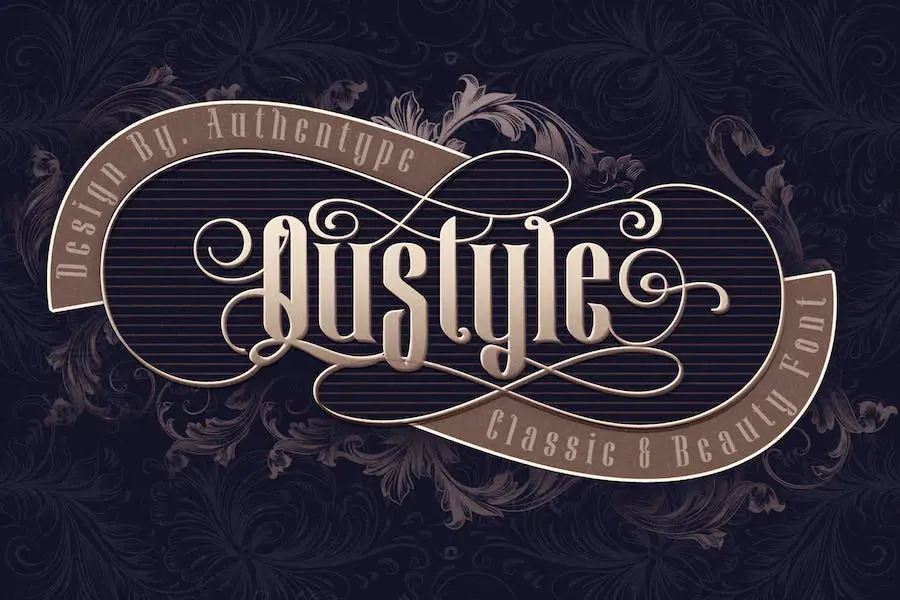
Qustyle是Authen Type设计的经典字体,为您的设计项目带来优雅和永恒的风格。
凭借其美丽而多样的字体概念,该字体非常适合创建令人惊叹的小册子、徽标和邀请函,传达精致和魅力的感觉。
无论您是从事品牌设计还是想为任何项目增添一丝优雅,Qustyle 都是将您的设计提升到新高度的字体。
杰姆洛克
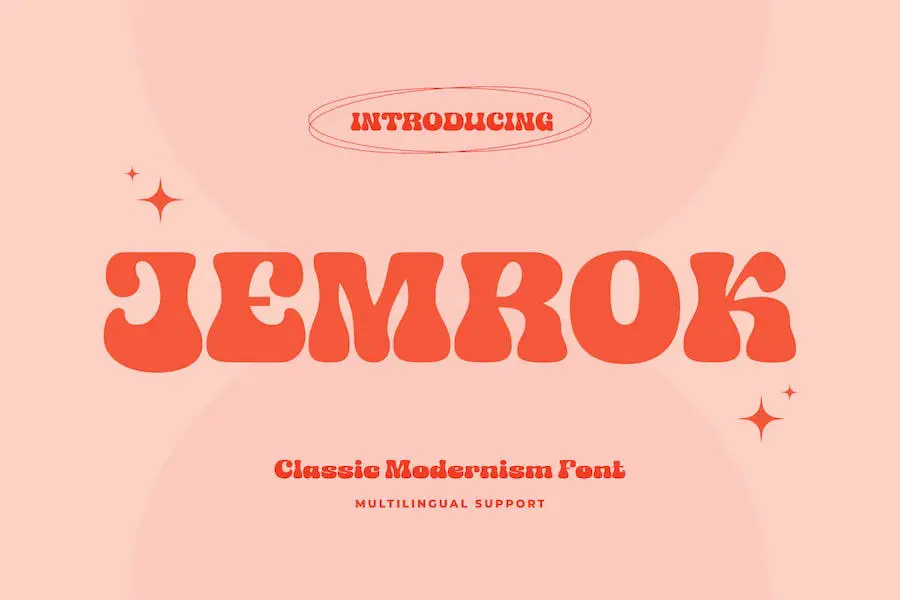
如果您是一名图形设计师,正在寻找完美的字体来增强您的项目,那么 JEMROK 就是您的最佳选择。 这种多功能字体非常适合徽标、海报、网站和任何其他需要经典现代主义风格的设计。
JEMROK 以其经典与现代元素的独特融合而从其他显示字体中脱颖而出。 大胆而有影响力的角色非常适合通过标题、标题和品牌来吸引注意力。
另外,这种字体提供了一系列不同的字符和替代品,提供了无限的创意可能性。 JEMROK 以其令人惊叹的优雅设计,体现了经典现代主义的精髓。
前线
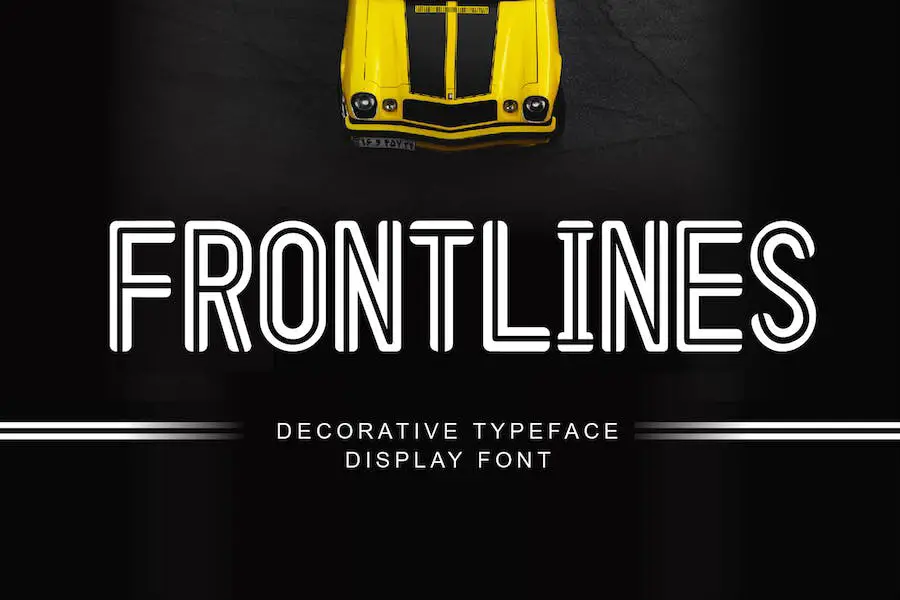
Frontlines 是一种多功能字体,可以将您的图形设计项目提升到一个新的水平。 它非常适合任何类型的设计项目,无论是卡片、电子贺卡、徽标、标题、海报还是标签设计。 Frontlines 以其经典而优雅的衬线风格为您的设计带来一丝精致。
Frontlines 提供永恒的外观,非常适合需要优雅和品位的项目。 它的多功能性使其能够在各种环境中大放异彩,从报纸和杂志广告设计到纹身排版。 借助 Frontlines,您可以创建既美观又具有影响力的设计。
格拉蒂克斯·罗宾娜
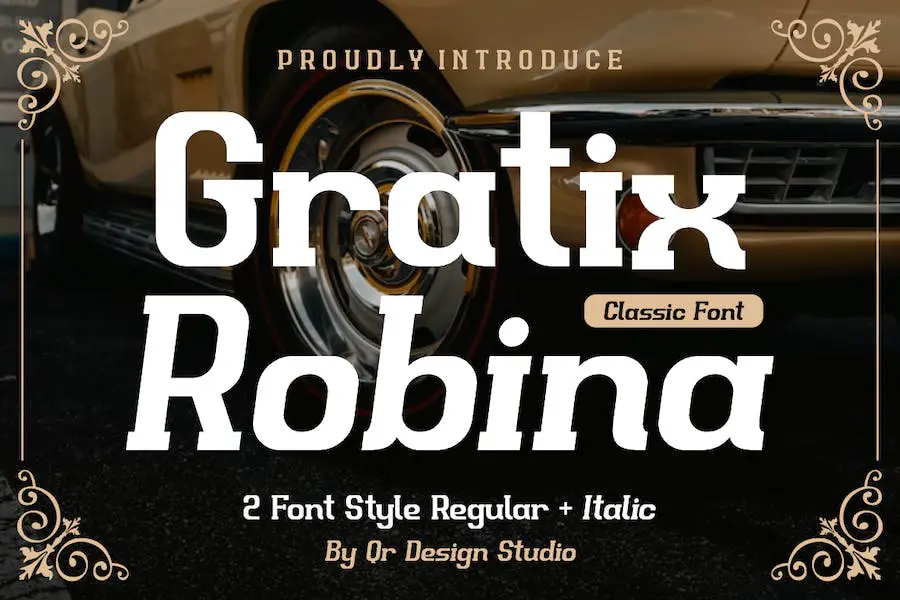
Gratix Robina 是一种大胆而真实的显示字体,被称为 It – Classic Font。 它非常适合各种品牌项目,例如复古、复古、海报、徽标、体育等。 凭借其多功能性,这种字体在任何情况下都能脱颖而出。
该字体大胆而真实的风格为您的设计增添了一丝怀旧气息。 无论您是在从事复古风格的项目还是想要创建经典徽标,Gratix Robina 都能满足您的需求。 其独特的魅力将使您的设计脱颖而出。
借助 Gratix Robina,您可以轻松创建引人注目的海报,捕捉过去时代的精髓。 该字体的复古氛围为您的设计带来真实和怀旧的元素,使它们具有视觉吸引力和令人难忘。
马尔马莱德
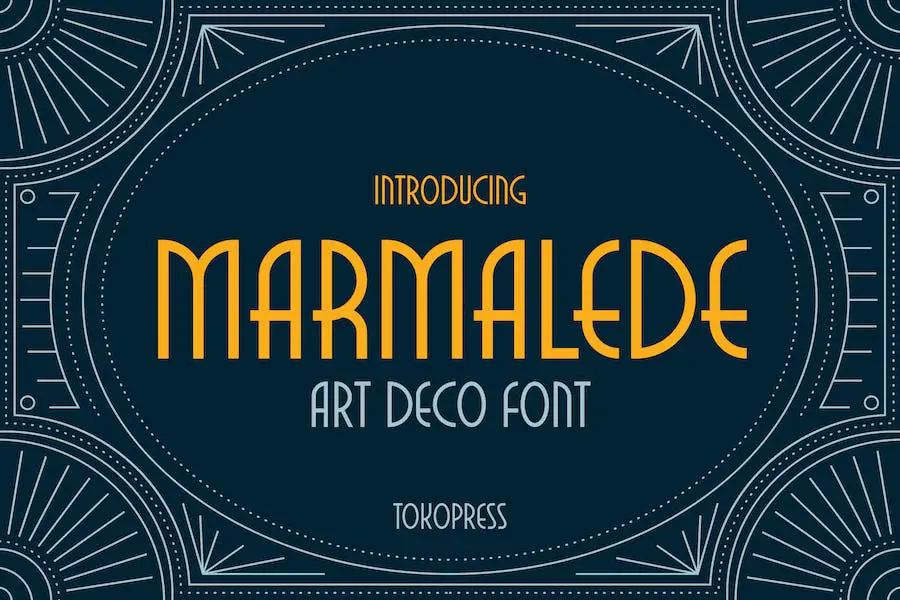
Marmalede 是一种散发着经典和优雅气息的字体,使其成为一系列设计项目的理想选择。
无论您是要创建高端海报、迷人的电影标题、优雅的餐厅/咖啡馆菜单、迷人的杂志布局、引人注目的 YouTube 封面和缩略图,还是令人惊叹的社交媒体页面封面,Marmalede 都是完美的选择。
凭借其装饰艺术美学,该字体旨在为您的项目带来永恒而精致的感觉。
诺凯尔
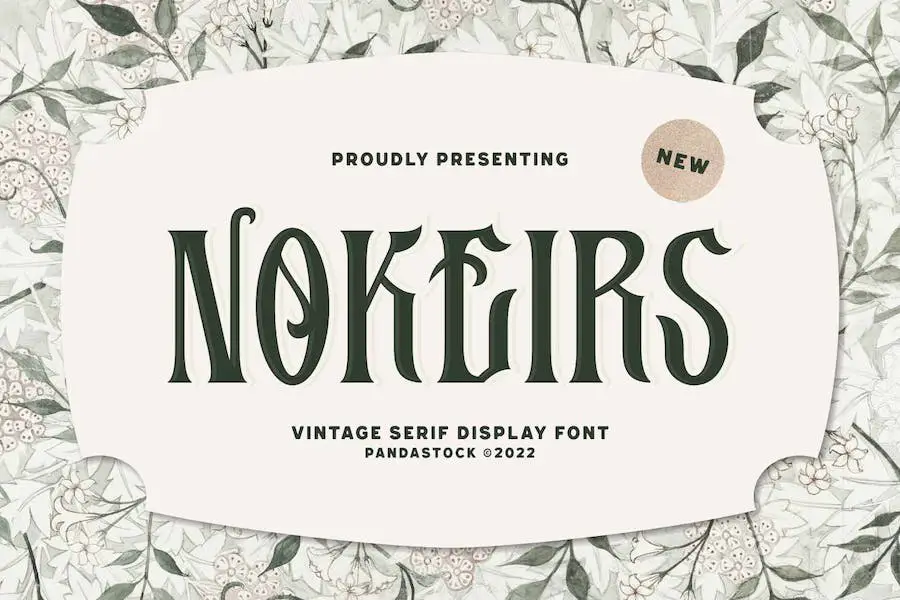
Nokeirs 是一种高度通用的字体,可以增强任何项目的设计,无论是小型邀请函还是大型品牌活动。
它是标志设计、杂志布局、摄影项目、产品包装等各种创意活动的完美选择。
这种现代经典字体以其优雅流畅的曲线,为您的作品增添一抹视觉优雅,使其脱颖而出并吸引注意力。
哈莉
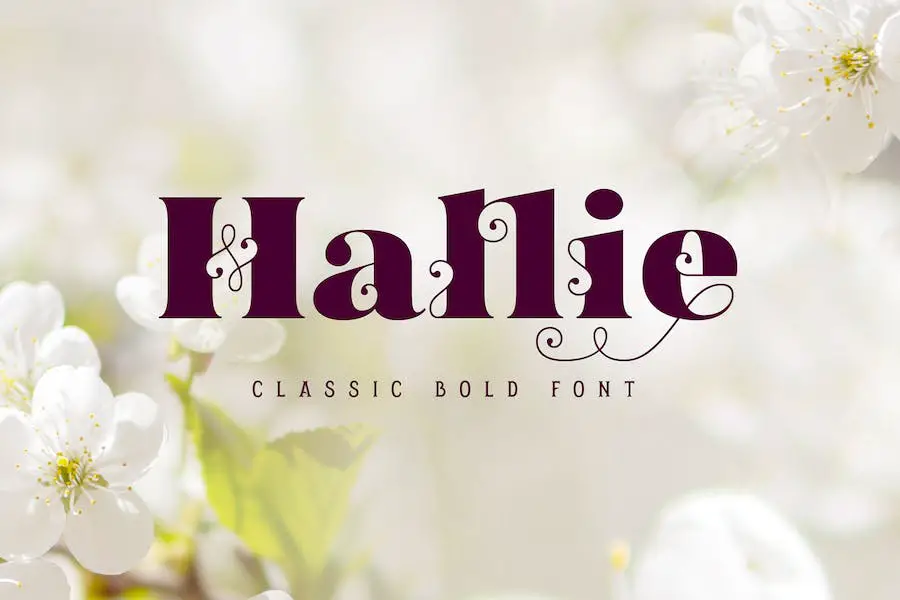
Hallie 是一种新的经典粗体字体,为您的项目带来一丝优雅。 凭借其高对比度的形状和细卷曲元素,它毫不费力地结合了复古和现代风格。
凭借大量的连字和花体符号,它允许您创建独特且原创的字体组合。 无论您是从事标签还是明信片设计,Hallie 都是提升项目美感的完美选择。
大师
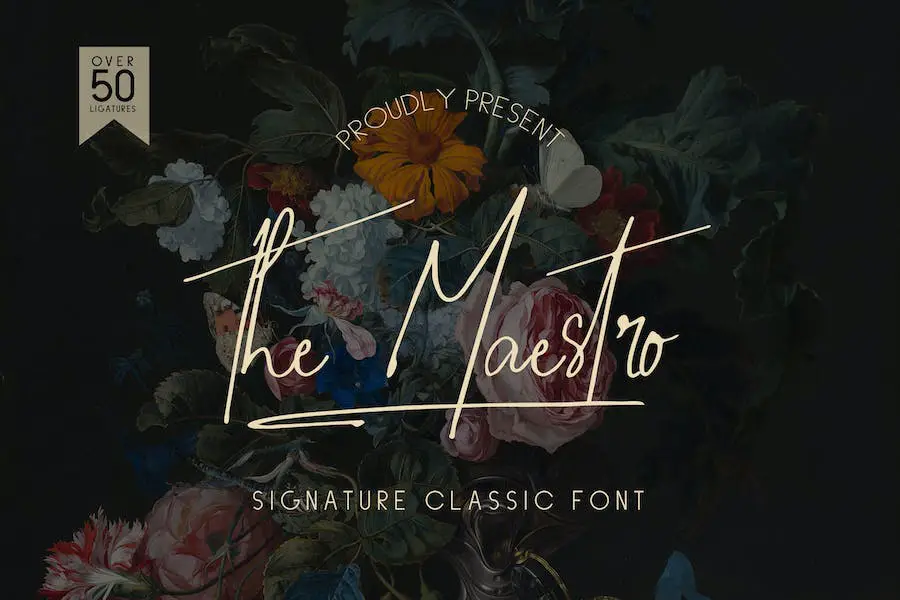
Maestro 是一款签名经典字体,非常适合徽标、徽章、邀请函和广告等各种设计项目。 它散发着优雅和精致的气息,适合奢华和现代主题的设计。
凭借其多功能性和永恒的吸引力,Maestro 是希望通过经典风格提升其项目的平面设计师的必备品。
昆西·琼斯
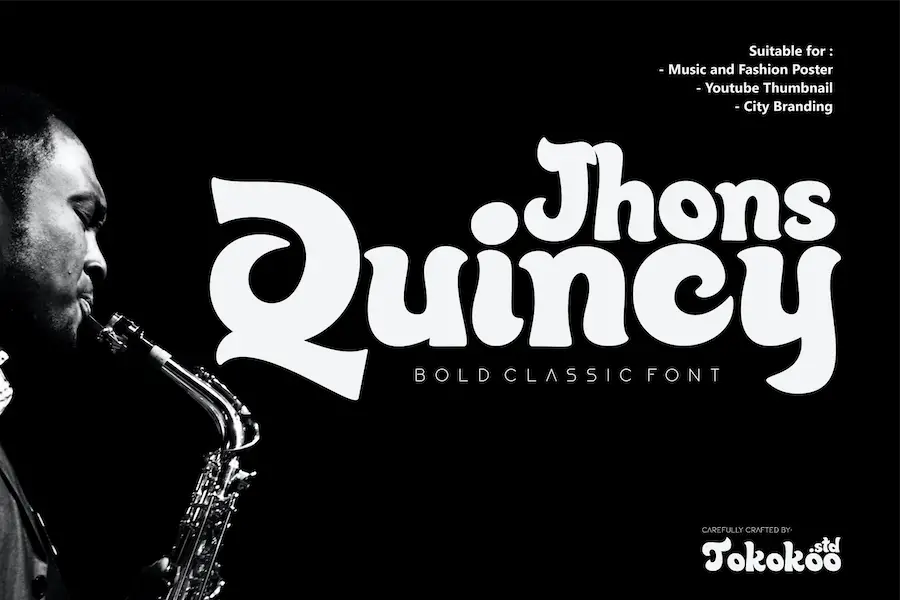
Quincy Jhons 以其有机的曲线和圆角,在每个字母中都散发着自然和人性化的气息。 这种字体有一种大胆而自信的态度,但它也无可否认地性感,很像爵士乐旋律的律动,在你的灵魂深处产生共鸣。
其圆润而有力的形状不仅增强了可读性,而且作为标题留下了持久的影响。
要充分利用 Quincy Jhons,请将其与简单的无字体搭配。 这两种字体在一个类型系统中和谐地协同工作,以强调重点、吸引注意力,并为您的设计注入个性。
古典
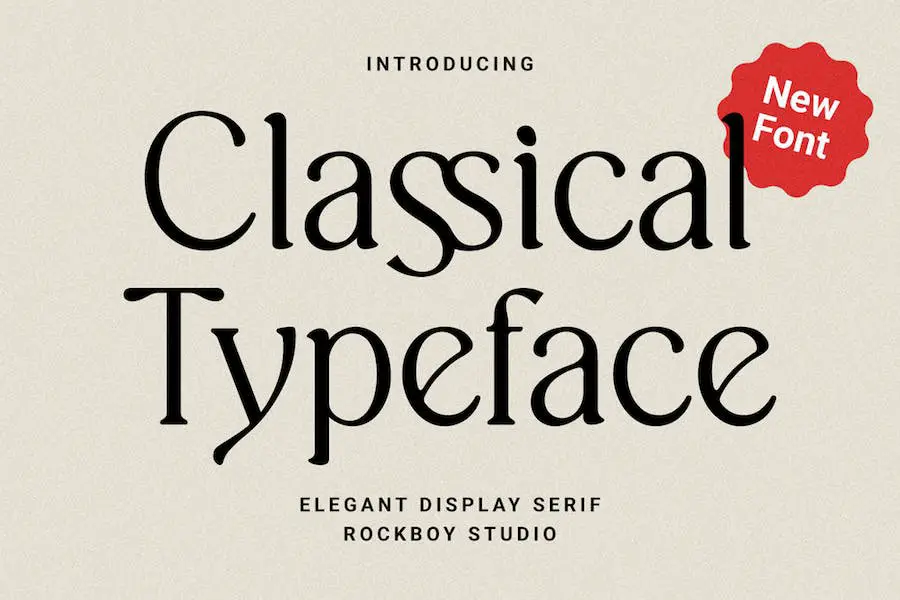
Classical Typeface 是一种经典的衬线字体,适合各种设计项目,如徽标设计、品牌、网页设计、包装,甚至社交媒体。 它为任何项目增添了一丝优雅和精致,使其脱颖而出并留下持久的印象。
凭借其永恒的外观,这种字体是寻求增强创意工作的图形设计师的必备品。 无论您是在制作专业徽标还是社交媒体帖子,经典字体都会将您的设计提升到一个新的水平。
暗升
Darkrise 是一款结合了经典字体和机车风格的字体,为您的设计带来动感和大胆的外观。
凭借其锋利的边缘和金属风格的设计,Darkrise 非常适合徽标、标题、标题、标签、T 恤、海报等。 它为任何项目增添了一丝锋芒和个性。
哈伦
Hallen 是一种提供一系列独特的花体和替代字体的字体,使其非常适合改进设计项目中的版式。 其规则而流畅的风格是现代主题的绝佳选择,而粗犷而有质感的风格则非常适合营造经典感觉。
无论您是在制作标识、杂志、海报、包装、品牌、网站、报价、邀请函还是任何定制设计,这种字体都会给您的创作带来专业和时尚的外观。
只需输入一些文字,即可发挥您的创造力,为您的项目创建完美的布局。
光荣者
Glorious 是一款令人惊叹的字体,无缝融合了现代和经典风格。 该字体具有大写和小写字母以及时尚的斜体版本,为您的设计项目提供了无限的可能性。
无论您是想创造永恒的作品还是为您的作品增添现代气息,The Glorious 都能满足您的需求。 常规和斜体样式的组合增添了酷炫和怀旧的感觉,将使您的设计脱颖而出。
那么为什么不尝试一下 The Glorious,看看它如何将您的项目提升到一个新的水平呢?
伯纳黛塔
Bernadetta 是一种现代而美丽的显示衬线字体,提供两种样式:常规和斜体。 凭借其字形变化,包括替代和连字,该字体允许您创建完美的版式设计。
它非常适合各种设计项目,例如徽标、品牌、广告、产品设计、文具、杂志设计、书籍和封面标题、摄影、艺术报价、婚礼设计、时装设计和特别活动。
Bernadetta 的多功能性使其适用于标签、产品包装等。
月球世界
Lunar World 是一种可以增强您所有图形设计项目的字体,无论您是在制作徽标、品牌、广告,甚至是书籍封面。
它具有多功能吸引力,可以满足从老式车库设计到现代品牌的各种设计需求。
您可以将其用于冒险和登山品牌、硬核音乐美学、动画电影、复古夏季海报引言、编辑设计、网站、博客等。
经典盒式磁带
Classic Cassette 是一种经典的显示字体,可为您的图形设计项目增添一丝优雅和风格。 凭借其精美的曲线和永恒的设计,这种字体非常适合为您的作品带来怀旧感和精致感。
Classic Cassette 的突出特点之一是其广泛的替代角色。 这些字符可以通过各种类型的功能来访问,例如花体、文体集、文体替代、上下文替代和连字。
这意味着您可以轻松自定义文本以满足您的特定需求,并创建真正独特且引人注目的设计。
死头
Deadhead 是一款令人愉悦的衬线字体,其灵感来自 60 年代和 70 年代复古广告中的迷人字母。 该字体拥有 300 多个字形,非常适合为您的设计项目增添一丝怀旧气息。
无论您是制作复古主题海报还是创建复古风格的徽标,Deadhead 都提供了多种选项来提升您的设计。 让我们深入了解这种经典字体的奇妙属性。
《Deadhead》最突出的一点是它俏皮有趣的氛围。 精心制作的字体唤起一种怀旧之情,立即将您的观众带回到 60 年代和 70 年代的时髦时代。
经典浪漫
Classic Romantic 是一种大胆的手写字体,可为任何设计项目增添一丝优雅。 这种多功能字体非常适合标题和文本块,非常适合网络和打印应用程序。
无论您是创建网站、设计宣传册还是制作视频,Classic Romantic 都会让您的文字看起来绝对令人惊叹。 凭借其最大和最小的变化,它提供了广泛的样式来满足每种设计需求。
准备好使用这款出色的字体将您的项目提升到一个新的水平。
经典正宗
Classical Authentic 字体是一种时尚、经典、复古、简单、优雅的字体,非常适合任何设计项目。 凭借其多功能的设计,该字体可以增强您的创意并为其增添一丝精致感。
无论您是在设计徽标、海报、杂志展示还是任何其他创意领域,这种字体绝对是一个有价值的工具,可以让您的设计栩栩如生。 其永恒的吸引力将吸引您的受众并使您的项目脱颖而出。
Classical Authentic字体的魅力在于它能够毫不费力地融入各种设计风格。 其经典复古的元素给人一种怀旧的感觉,而简约优雅又带来现代的气息。
凯奥拉